산돌구름 = 베이키?
산돌은 누구나 자유롭게 표현할 수 있는 세상을 위해 다양한 서비스를 제공하고 있어요. 대표적으로 ‘산돌구름 웹’과 ‘산돌구름 모바일 앱’이 있는데요. 두 서비스는 매체의 차이뿐 아니라 상품도 타겟도 전혀 달라요. 대부분의 디자이너는 ‘산돌구름 웹’이 더 익숙하실 텐데요. ‘산돌구름 웹’과 달리 ‘산돌구름 모바일 앱’은 ‘엔터테인먼트 폰트(모바일 폰트)’만을 제공하고 있어요. 기존의 폰트가 일의 도구로 사용되었다면 ‘엔터 폰트’는 '나'를 표현하는 수단이라는 점이 두 상품의 차이점이죠.
서비스를 이용하는 목적이 다르니 사용자 경향은 다를 수밖에 없고, 타겟이 다르면 상품도 달라질 수밖에 없죠. 이렇게 다른 두 서비스가 ‘산돌구름’이라는 같은 이름으로 불리니 안팎으로 혼란스러운 지점들이 있었어요. 그 경계를 명확히 하고, ‘엔터 폰트’를 통해 나다움을 탐색하고 표현할 수 있는 세상을 만들어 가기 위해 산돌은 ‘산돌구름 모바일 앱’을 리뉴얼 했어요. 오늘은 ‘산돌구름 모바일 앱’이 ‘베이키’로 다시 태어난 과정을 들려드릴게요.
레시피 1. 계량: 브랜드 정의
리뉴얼에 앞서 사용자들이 ‘산돌구름 모바일 앱’을 어떻게 인식하고 있는지 객관적인 정보가 필요했어요. 앱 내 설문조사를 통해 사용자 연령대, 성별, 직군, 사용 경향, 제품 선호도 등을 수집했어요. 결과를 살펴보니 우리의 가설과 같은 지점도 있었고 다른 지점도 있었어요. 하지만 브랜드의 가장 큰 뼈대가 ‘심미적 만족감을 위한 서비스'임에는 변함이 없었죠. 이 외 간극이 있는 부분은 과정에서 메꿔나가며 프로젝트가 본격적으로 진행됐어요.
가설 검증에 이어 경영진과의 토론 자리를 마련했어요. 앞으로 가야 할 방향을 더 선명하게 그리기 위한 자리였어요. ‘왜?’와 같은 가장 근본적인 질문에 답변을 찾고 뼈대를 만들 수 있었죠. 더불어 모두가 같은 방향을 보고 있는지 확인하기 위해 내부인 인터뷰도 진행했는데요. 우리는 우리를 잘 안다고 생각하지만 ‘왜 서비스를 제공하나요?’, ‘지향점은 무엇인가요?', ‘강점은 무엇인가요?’와 같은 질문들을 마주하면 그렇지 않다는 걸 체감해요. 인터뷰는 이같은 원초적인 질문에 답변을 찾아가며 브랜드와 서비스에 대해서 깊이 생각하게 해요. 저 역시 이 과정에서 브랜드가 지향하는 바를 깊이 고민하고 내재화할 수 있었어요.
구성원들은 [모바일 환경에서 폰트 사용 제약을 최소화해 쉽게 사용할 수 있는 서비스], [‘나'를 표현하고 싶은 이들의 니즈를 만족시키는 플랫폼]에 대한 지점을 공통되게 이야기하고 있었어요. 저는 이것을 ‘고유함을 자유롭게 표현할 수 있도록 돕겠다는 의지’라고 표현했는데요. 산돌이 추구하는 ‘누구나 자유롭게 표현할 수 있는 세상’과도 맞닿아 있는 지향점이에요. 산돌의 비전을 서비스만의 방식으로 이어가고 있음을 확인하며 현황 분석을 종료했어요.
레시피 2. 반죽: 네이밍
앞서 수집한 데이터들을 바탕으로 우리는 ‘마음껏 나다움을 탐색하고 표현할 수 있는 세상’을 꿈꾸고 있음을 확인했어요. 이를 위해 우리는 이미 ‘취향을 발견할 수 있는 공간'과 ‘나다움을 표현할 수 있는 도구’를 제공하고 있어요. 바로 ‘산돌구름 모바일 앱’이라는 플랫폼과 ‘엔터 폰트’에요. 방향을 명확히 했으니 이 결에 맞는 새로운 이름을 지을 단계에요. 서두에서도 말했듯, 산돌구름과 완전히 구분되면서도 산돌의 헤리티지를 계승할 수 있는 이름이 필요했어요. 더해, ‘엔터 폰트’라는 즐거운 세계에 어울려야 했죠.
수많은 후보 중 최종적으로 선택된 이름은 ‘베이키(Bakey)’에요. ‘Bakery’에서 비롯된 이 이름은 ‘폰트를 디저트처럼 즐기는 시각적 경험’을 상징해요. 다양한 맛의 디저트가 미각을 자극하듯, 베이키는 다양한 폰트를 통해 시각적 즐거움을 제공하겠다는 의미를 담고 있어요.
레시피 3. 굽기: 상징화
로고타입은 다양한 형태를 스터디 했는데요. 베이키가 추구하는 가치를 직관적으로 보여줄 수 있는 장식적인 형태부터, 다양한 개성을 담아낼 수 있도록 캐릭터가 강하지 않은 버전까지 테스트했어요. 이 중간 지점을 찾아 웨이트 테스트도 진행했어요. 1차적으로 결정된 로고타입을 Light, Regular, Bold 세 개의 축으로 파생해 배리어블 폰트로 제작했어요. 획의 섬세함이 관찰되면서도 브랜드 인지가 명확히 되는가를 기준으로 웨이트를 결정했어요.
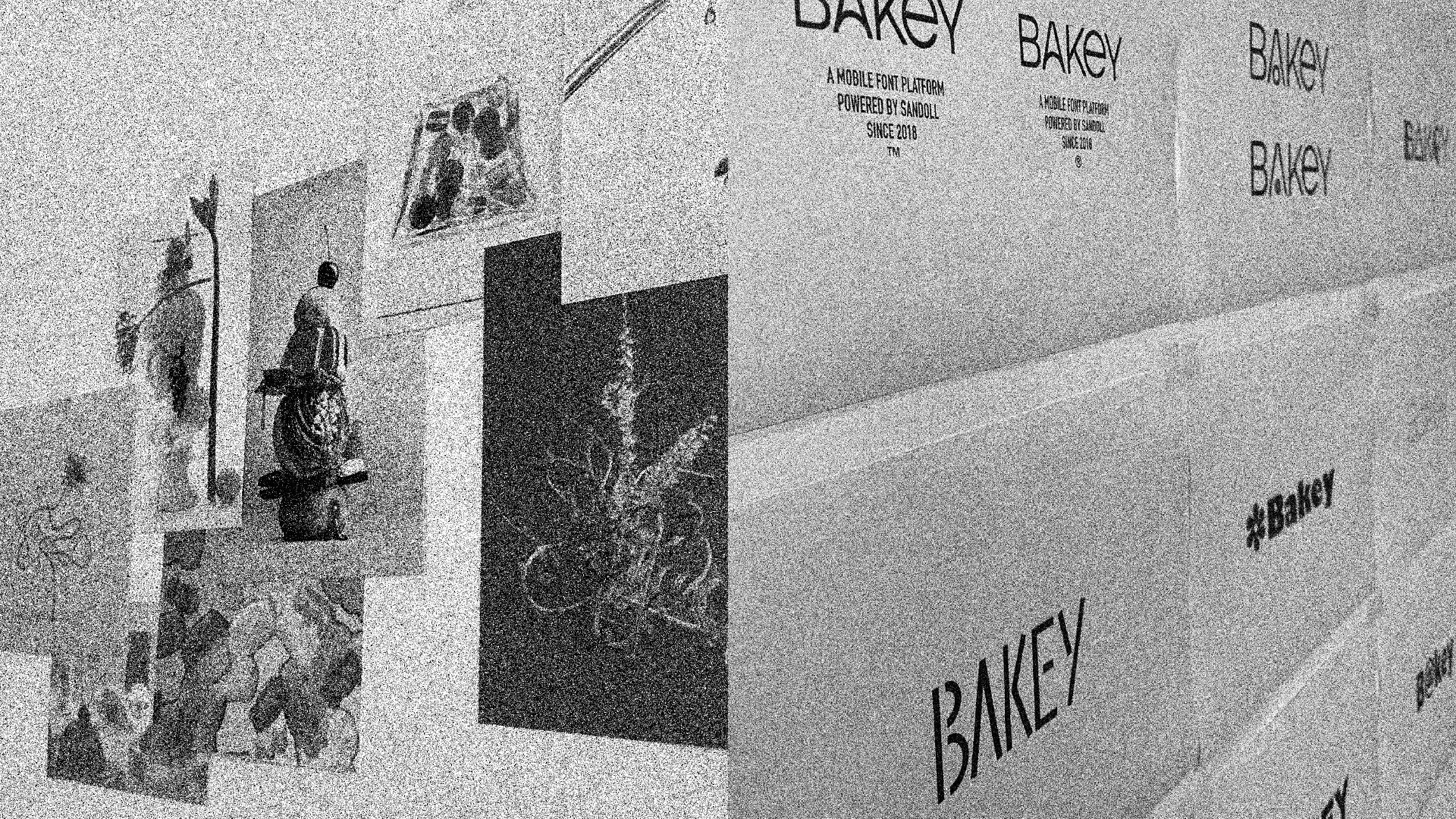
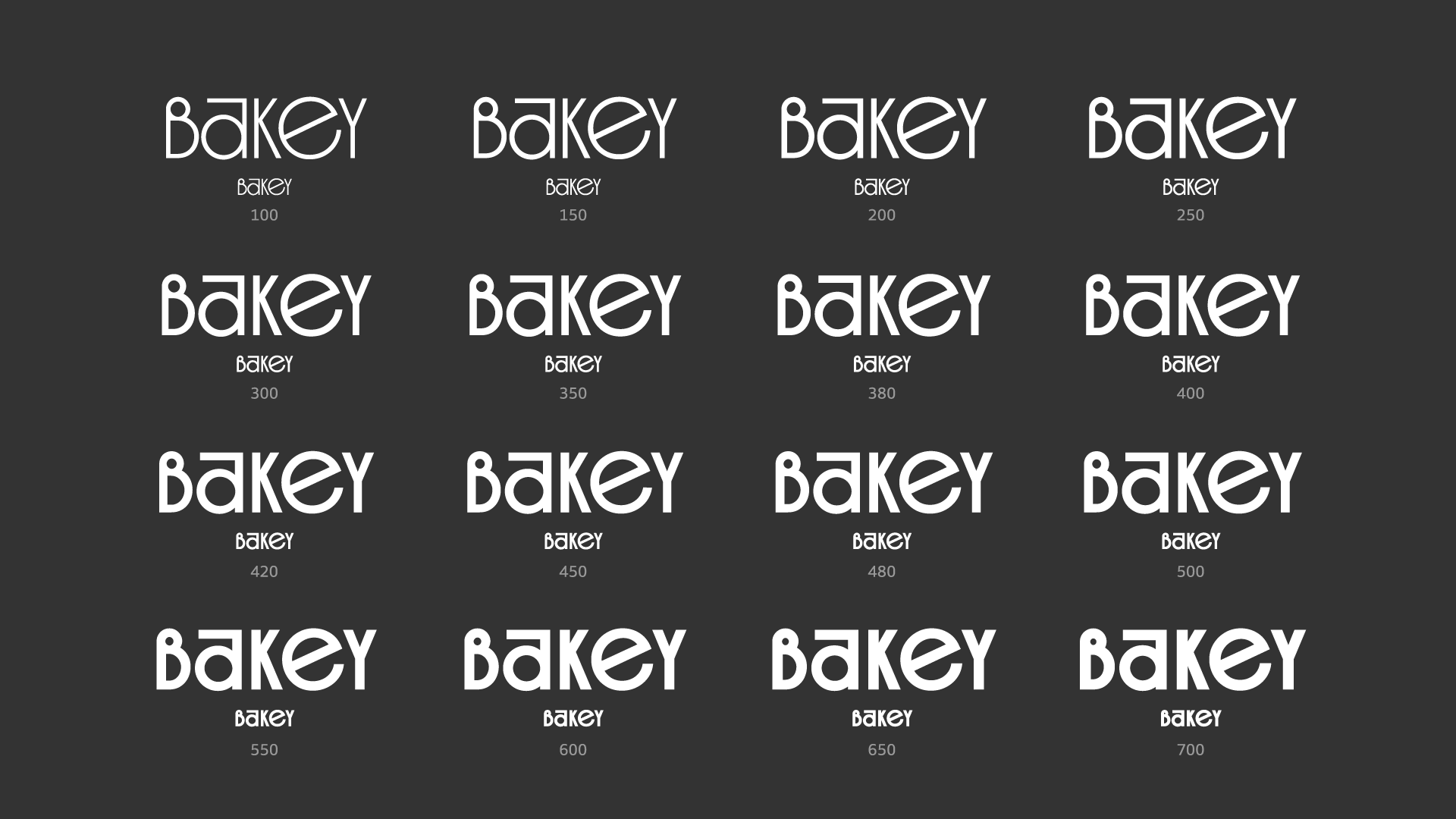
최종 로고타입은 대소문자, 자폭, 기울기 등이 다른 알파벳이 모여 하모니를 이루는 구조인데요. ‘다양한 개성이 조화롭게 공존하는 플랫폼'을 시각적으로 표현했어요. 특히 ‘e'는 '즐거움’의 가치를 상징적으로 담고 있어요. 열린 속공간이 웃음이 가득한 사람의 입 같지 않나요?
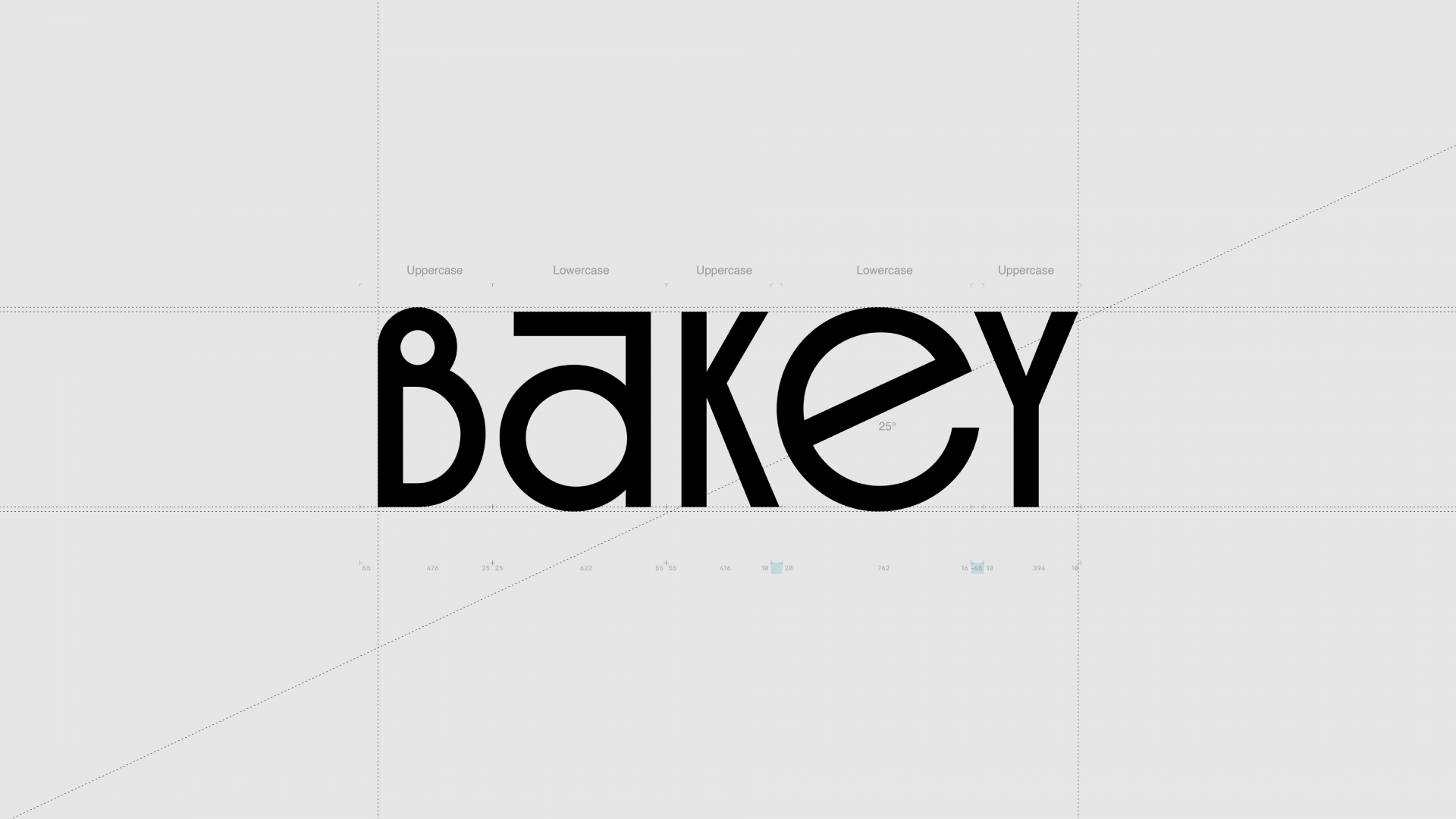
레시피 4. 장식: 시각화
베이키의 메인 컬러는 ‘Strawberry Red’ 에요. 생동감과 활력을 담은 이 컬러는 산돌 레드에 그 뿌리를 두고 있어요. 여기에 베이키의 아이덴티티를 더해 핑크빛이 도는 레드를 메인 컬러로 결정했는데요. 케이크에 장식되는 딸기나 체리 같은 달콤한 레드를 표현하려고 했어요. 보조색으로는 브라운, 블루, 옐로우를 함께 사용해 단조로움을 피하고 다채로운 이미지를 표현했어요.
베이키의 그래픽은 브랜드 정체성을 가장 직관적으로 보여주고 있어요. 다양한 재료, 질감, 컬러로 이뤄진 디저트는 ‘엔터 폰트’를 의미해요. 누군가는 과일이 가득 들어간 초콜릿 케이크를 좋아하고, 누군가는 고소한 통밀 향이 나는 담백한 식빵을 좋아하죠. 폰트도 마찬가지예요. 귀엽고 화려한 폰트를 좋아하는 사람도 있고, 손으로 꾹꾹 눌러쓴 듯한 소박한 폰트를 좋아하는 사람도 있어요. 이런 다양성을 담은 플랫폼임을 시각적으로 전달하기 위해 그래픽을 활용했어요.
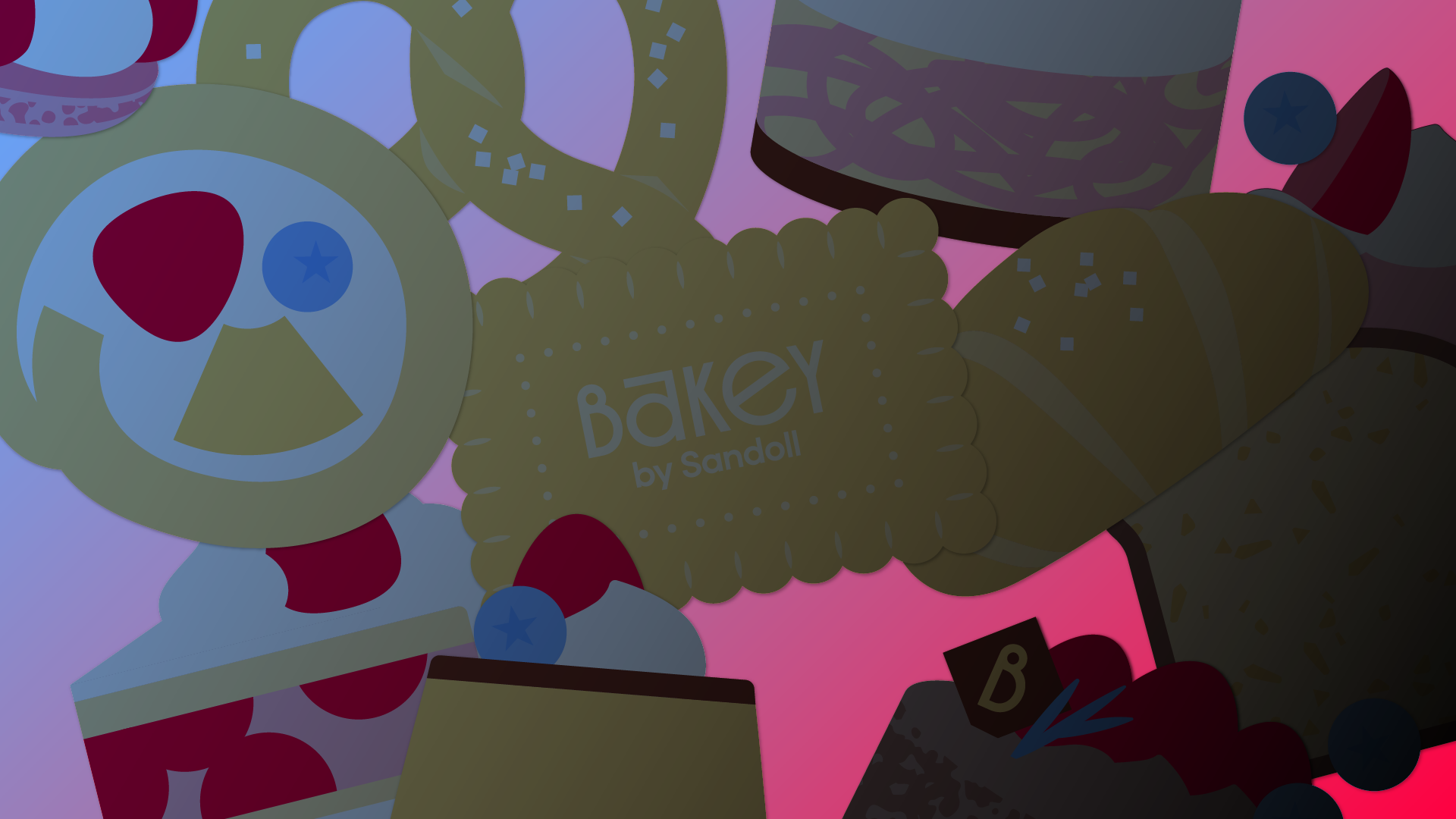
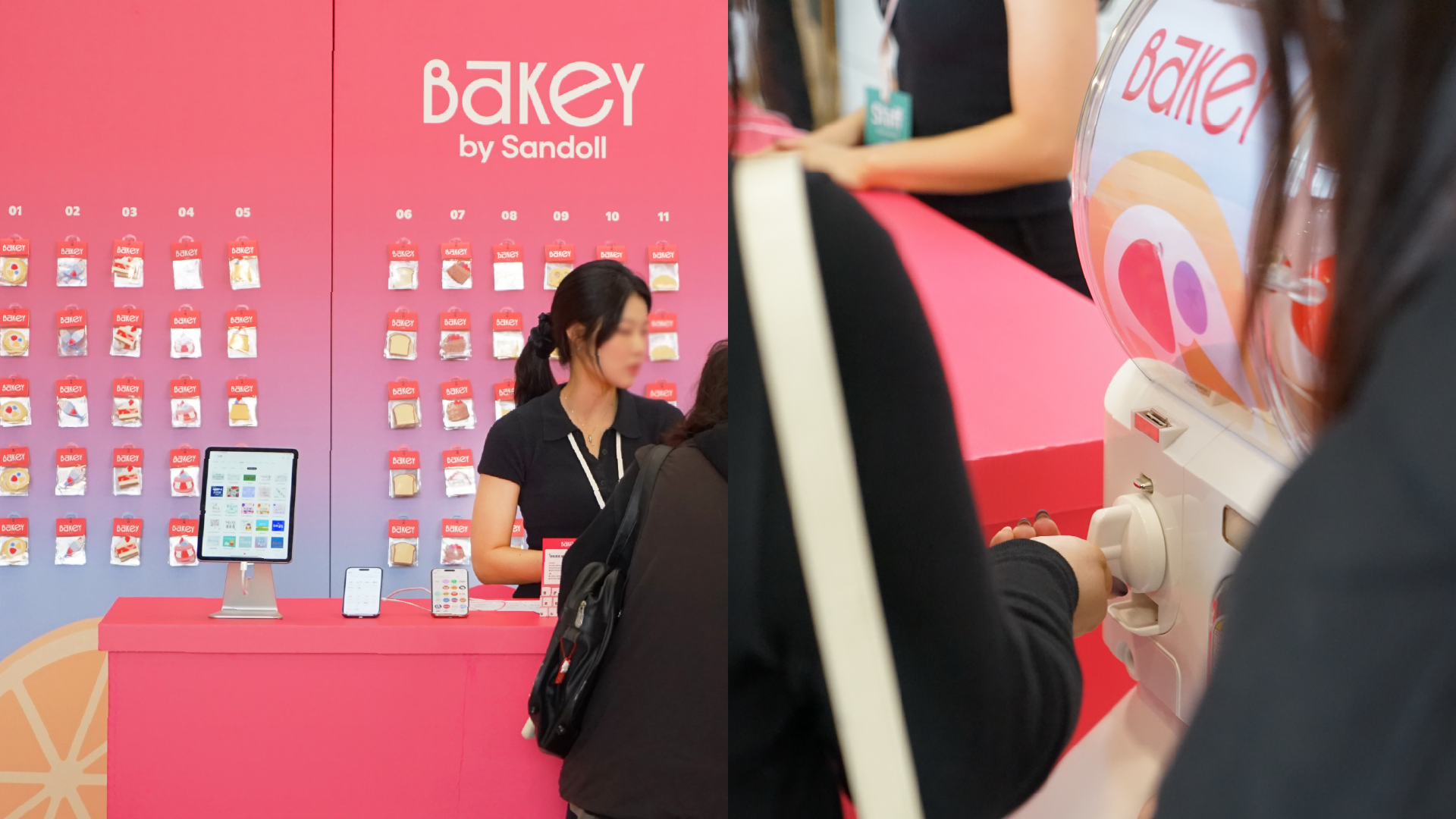
레시피의 다음 장
이번 리브랜딩은 단순히 이름이나 로고를 바꾸는 일이 아니라 폰트의 역할이 확장되는 전환점이었어요. 디자이너만의 언어로 여겨지던 폰트가 이제는 누구에게나 열려 있는 표현의 수단이 되었죠. 베이키는 이런 변화 속에서 폰트를 도구가 아닌 감각의 경험으로 바라보길 제안하고 있어요. 모바일이라는 가장 개인적인 매체를 통해 사용자가 자신의 취향을 발견하고 ‘나다움’을 표현할 수 있길 바라요.
앞으로 베이키는 ‘엔터 폰트’를 중심으로 취향과 감각을 발견하는 플랫폼을 만들어 가려고 해요. 한국어를 넘어 여러 언어와 문화가 섞인 공간에서도 폰트를 매개로 연결될 수 있다고 믿어요. 이처럼 베이키는 ‘폰트로 세상을 더 다채롭게 만드는 방법’을 계속 탐구하고 있어요. 폰트가 문화가 되고 다양한 ‘나다움’을 표현할 수 있는 세상을 꿈꾸며, 앞으로 베이키가 보여줄 다채로운 레시피를 기대해 주세요.